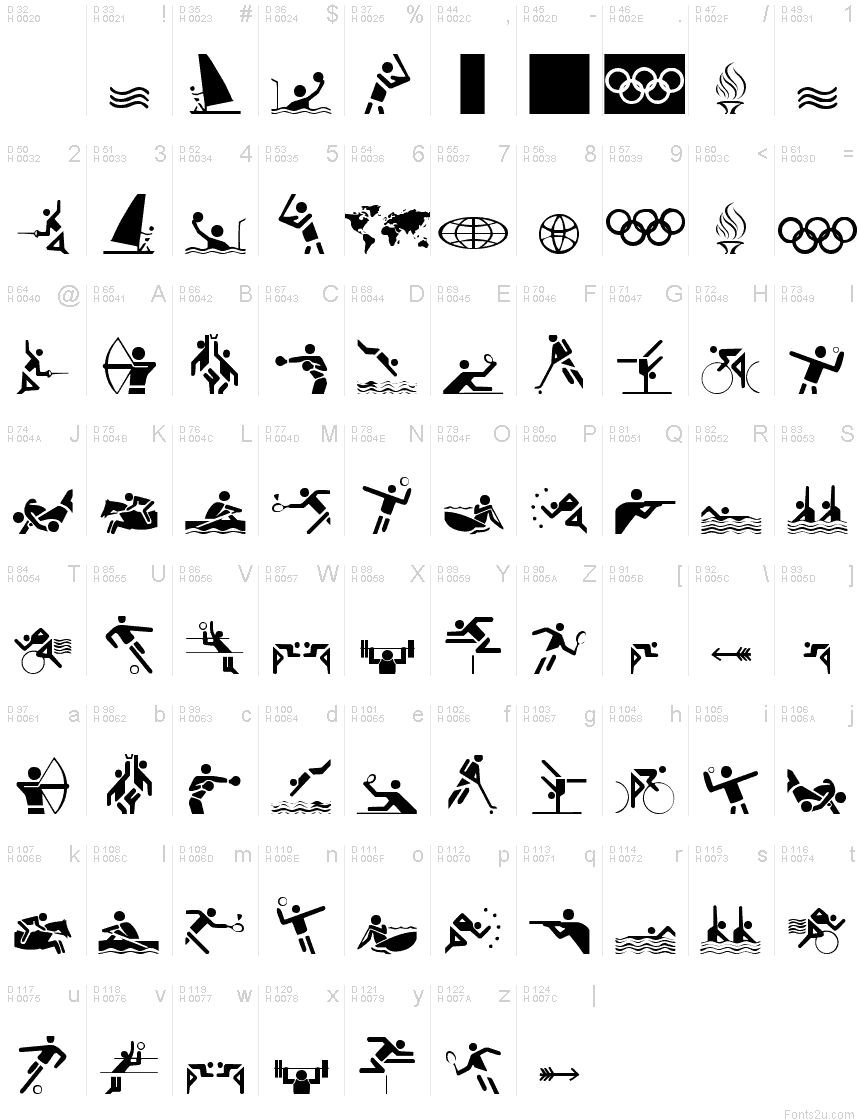
Olympicons Regular Шрифт
Olympicons от Iconian Fonts — это бесплатный спортивный шрифт-пиктограмма с четкими силуэтами атлетов и динамичными позами. Иконки выполнены в едином визуальном стиле: согнутые конечности, линии движения и детали инвентаря подчеркивают атмосферу соревнований и активности.
Olympicons идеально подходит для плакатов спортивных клубов, программ турниров, принтов на футболках, бейджей, веб-маркеров и приглашений с тематикой кубков — особенно когда в макете нужны быстрые спортивные акценты. Шрифт также отлично работает как разделитель разделов, маркировка или декоративный элемент в расписаниях и турнирных сетках, сохраняя целостность дизайна без лишнего визуального шума.